싸인은 단순한 서명이 아니라 개성과 스타일을 나타내는 요소예요. 더 세련된 싸인을 만들고 싶다면, 단계별로 정리하면서 개선하는 과정이 필요해요. ✍🔥
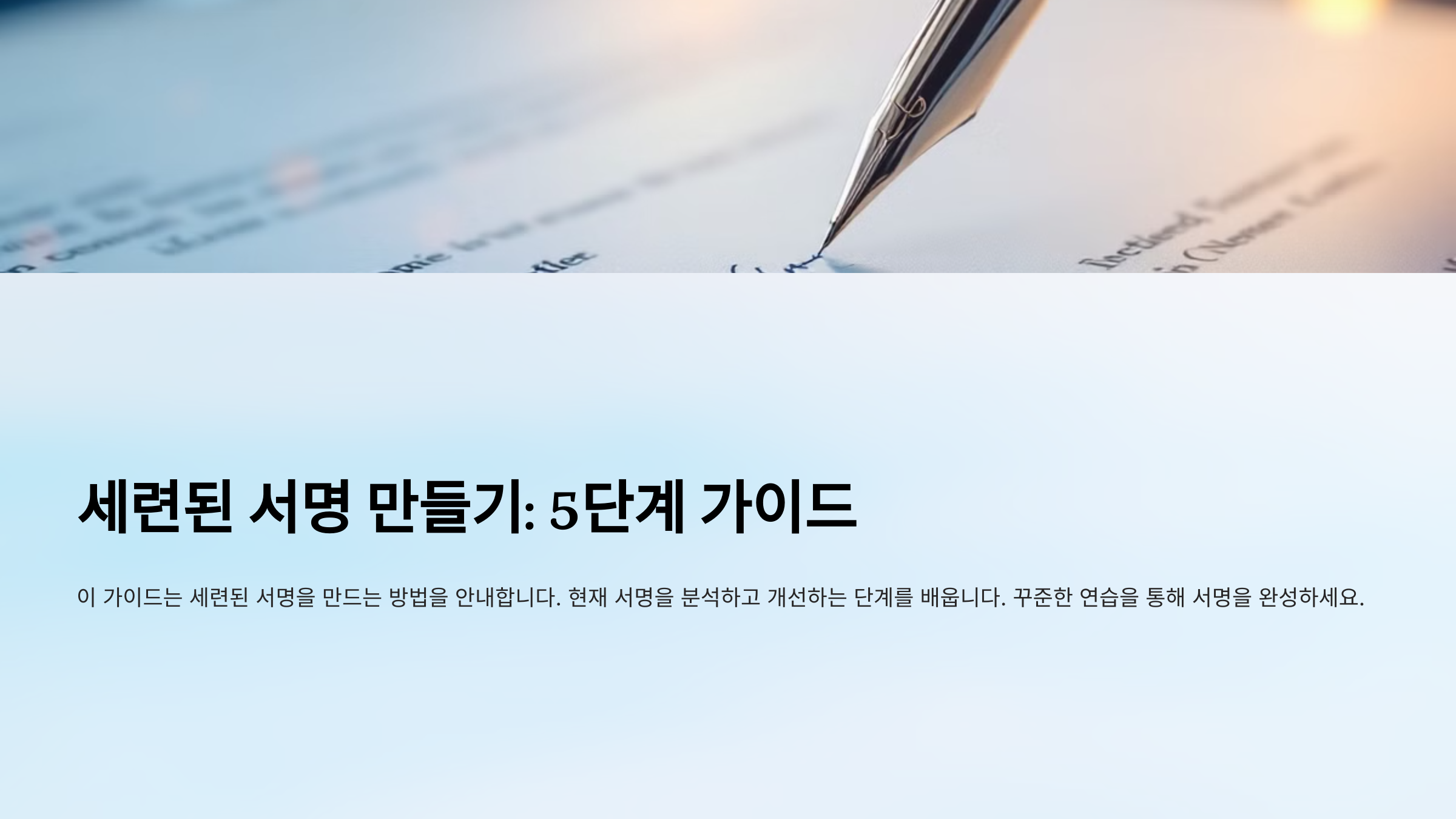
내가 생각했을 때, 멋진 싸인은 간결하면서도 독창적인 스타일을 유지하는 것이 중요해요. 이제 싸인을 세련되게 바꾸는 5단계 과정을 알아볼까요? 🚀
1단계: 현재 싸인 분석하기 🔍
현재 사용하고 있는 싸인이 있다면, 무엇을 개선할 수 있는지 분석하는 것이 첫 단계예요. 싸인을 평가할 때는 가독성, 속도, 디자인, 개성 등 여러 요소를 고려해야 해요. ✍
🔹 현재 싸인 점검 체크리스트
✔ 싸인을 빠르게 쓸 수 있는가?
✔ 동일한 스타일을 유지할 수 있는가?
✔ 내 개성이 잘 드러나는가?
✔ 가독성이 좋고 쉽게 알아볼 수 있는가?
📌 현재 싸인 분석 방법 ✨
분석 요소 확인할 사항 가독성 글자가 알아보기 쉽게 구성되었는가? 속도 5초 이내에 자연스럽게 싸인을 끝낼 수 있는가? 일관성 반복해서 쓸 때 같은 모양을 유지할 수 있는가? 개성 싸인에 나만의 스타일이 담겨 있는가? 이제 2단계: 불필요한 요소 제거를 진행해볼까요? ✂
2단계: 불필요한 요소 제거 ✂
싸인이 복잡하면 빠르게 작성하기 어렵고, 일관성을 유지하기 힘들어요. 따라서 불필요한 장식과 복잡한 획을 줄여주는 과정이 필요해요. ✍🔥
🔹 불필요한 요소 줄이는 방법
✔ 글자의 일부를 단순화하여 빠르게 쓰기
✔ 복잡한 장식(별, 밑줄 등) 제거하기
✔ 글자 간 간격을 조정하여 균형 맞추기
✔ 획을 줄이고 연결을 부드럽게 만들기
📌 단순하고 효율적인 싸인 만들기 ✨
불필요한 요소 개선 방법 복잡한 장식 별, 밑줄, 불필요한 곡선 삭제 획이 너무 많음 획을 최소화하고 간결한 형태 유지 글자 간 간격 불균형 균형을 맞춰 가독성 높이기 글씨체가 너무 꾸밈 필기체를 단순화하여 자연스럽게 변경 이제 3단계: 필기체 흐름 개선을 진행해볼까요? 🖊
3단계: 필기체 흐름 개선 🖊
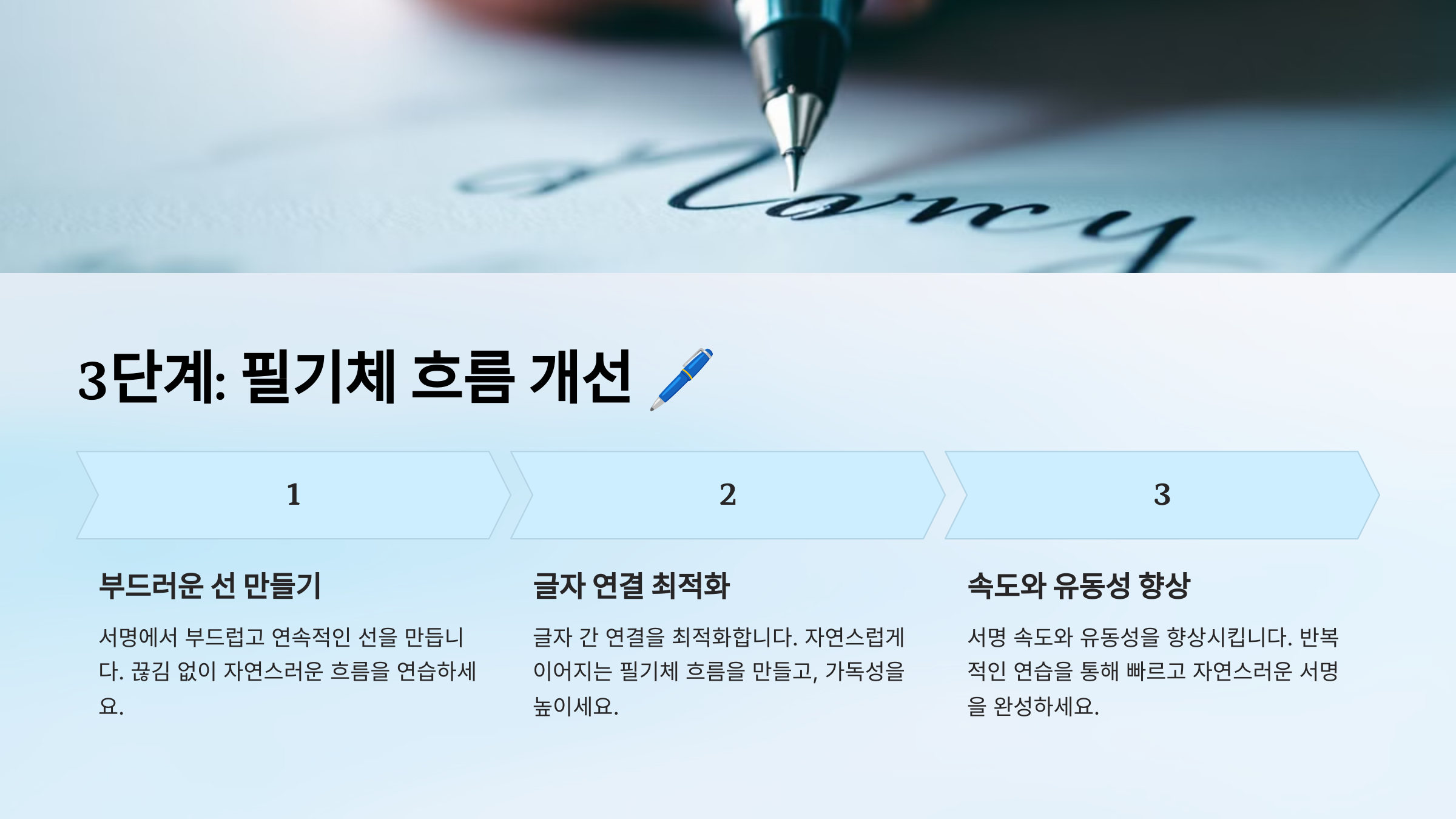
싸인을 세련되게 만들려면 필기체의 자연스러운 흐름이 중요해요. 획을 부드럽게 연결하면 속도가 빨라지고, 싸인이 더 깔끔해 보일 수 있어요. ✍🔥
🔹 필기체 흐름을 개선하는 방법
✔ 글자 간 연결을 부드럽게 이어지도록 연습하기
✔ 곡선을 활용하여 자연스럽게 흐름 만들기
✔ 필기 속도를 높여서 손에 익숙해지도록 연습하기
✔ 이니셜을 강조하고 나머지 글자는 간결하게 정리
📌 부드러운 싸인 흐름 만들기 ✨
필기체 흐름 개선 요소 설명 글자 간 연결 자연스럽게 이어지는 흐름 연습 곡선 활용 부드러운 곡선을 추가해 세련된 스타일 빠른 필기 연습 속도를 높여 자연스러운 흐름 만들기 이니셜 강조 첫 글자를 강조해 강렬한 인상 남기기 이제 4단계: 마무리 스타일 정리를 진행해볼까요? ✨
4단계: 마무리 스타일 정리 ✨
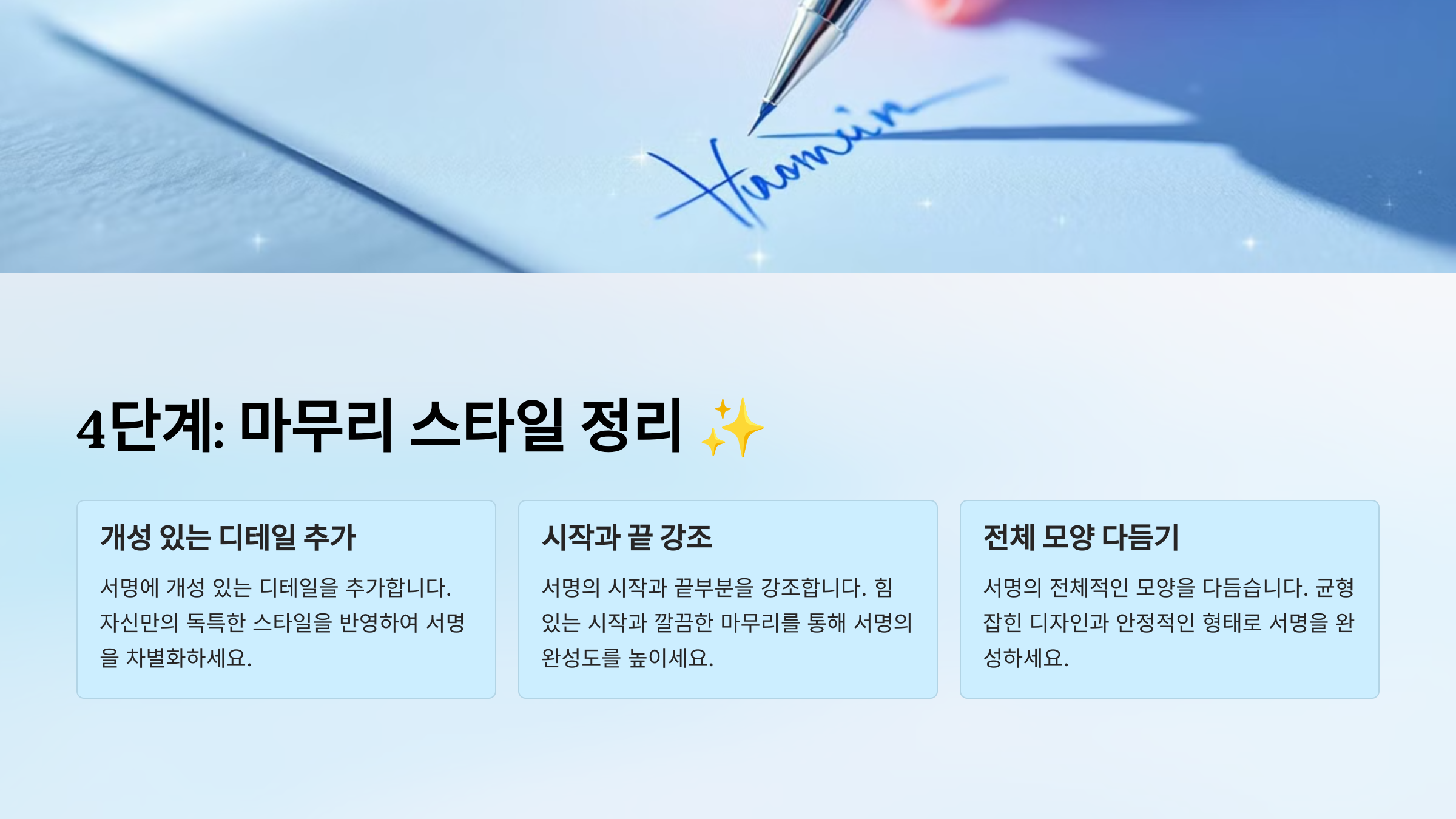
싸인의 마무리 부분은 전체적인 인상을 결정하는 중요한 요소예요. 끝을 어떻게 정리하느냐에 따라 세련된 느낌을 더할 수도 있고, 강렬한 인상을 남길 수도 있어요. ✍🔥
🔹 싸인 마무리를 세련되게 하는 방법
✔ 끝을 길게 빼서 부드러운 흐름 만들기
✔ 마지막 획을 날렵하게 정리하여 강렬한 느낌 주기
✔ 밑줄이나 작은 기호를 활용해 개성을 살리기
✔ 싸인의 크기를 일정하게 유지해 균형 맞추기
📌 싸인 마무리 스타일 ✨
마무리 스타일 설명 끝을 길게 빼기 싸인의 흐름을 부드럽게 이어주는 효과 날렵한 마무리 깔끔하고 강렬한 느낌 연출 기호 활용 별⭐, 점•, 밑줄━ 등을 추가해 개성 표현 균형 유지 싸인의 크기와 배치를 일정하게 유지 이제 5단계: 꾸준한 연습과 정착을 진행해볼까요? 📄
5단계: 꾸준한 연습과 정착 📄
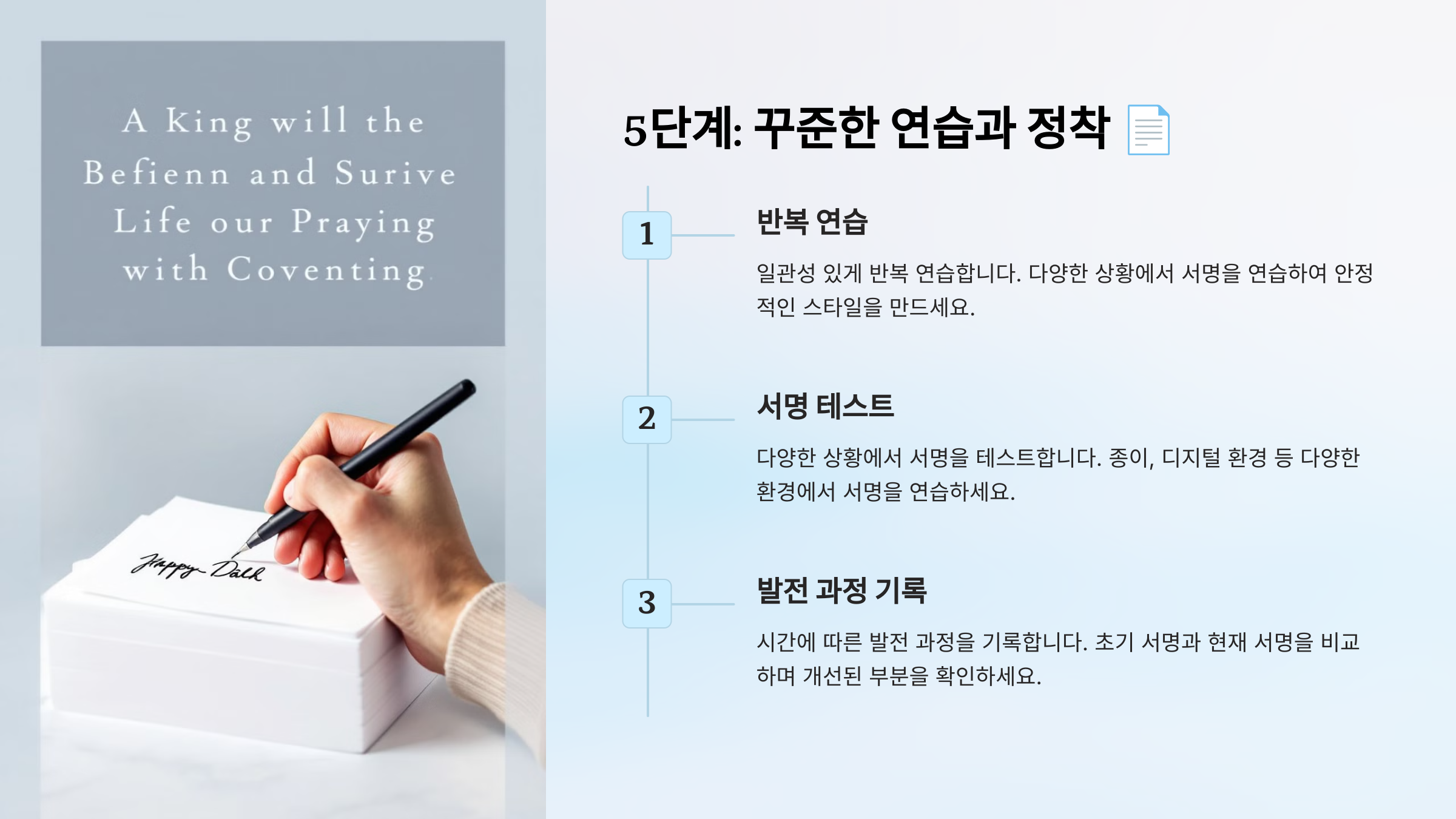
멋진 싸인을 만들었다면 꾸준한 연습을 통해 손에 익히는 과정이 필요해요. 자연스럽게 싸인을 작성할 수 있어야 어떤 상황에서도 일관된 스타일을 유지할 수 있답니다! ✍🔥
🔹 싸인을 정착시키는 방법
✔ 하루 5~10분씩 반복해서 연습하기
✔ 다양한 크기로 싸인을 연습하여 응용력 키우기
✔ 빠르게 작성하는 연습을 통해 자연스럽게 만들기
✔ 공식 문서에서도 동일한 싸인을 유지하도록 연습
📌 효과적인 싸인 연습법 ✨
연습 방법 설명 반복 연습 매일 10번 이상 싸인을 반복해서 연습 크기 조절 A4, 명함, 포스트잇 등 다양한 크기로 작성 속도 향상 5초 안에 싸인을 끝낼 수 있도록 연습 실제 문서 활용 계약서, 서류 등에 실제로 싸인해보기 이제 세련된 싸인 스타일 예시를 살펴볼까요? 🏆
세련된 싸인 스타일 예시 🏆
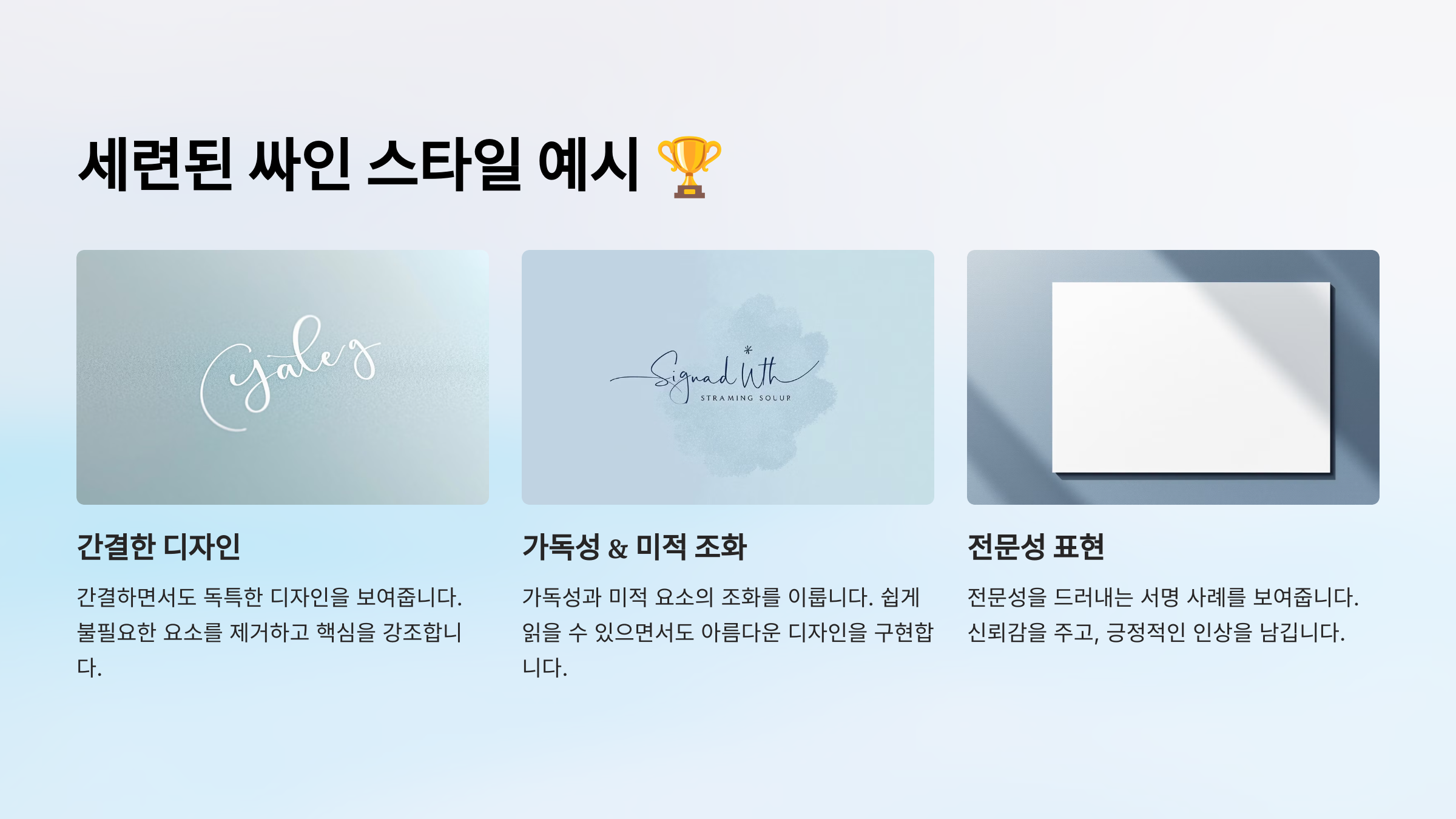
멋진 싸인을 만들기 위해서는 다양한 스타일을 참고하는 것도 좋은 방법이에요. 세련된 싸인은 단순하면서도 개성이 살아 있고, 자연스러운 흐름이 있어야 해요. ✍🔥
🔹 대표적인 싸인 스타일
✔ 이니셜 스타일 – 간결하고 빠르게 작성 가능
✔ 곡선형 스타일 – 부드럽고 자연스러운 느낌
✔ 대문자 강조 스타일 – 강렬한 인상을 남길 수 있음
✔ 미니멀한 스타일 – 단순하지만 고급스러운 느낌 연출
📌 싸인 스타일 비교 ✨
싸인 스타일 설명 이니셜 스타일 이름의 첫 글자만 사용하여 심플하게 구성 곡선형 스타일 부드러운 곡선과 자연스러운 흐름 강조 대문자 강조 이름 전체를 대문자로 강렬하게 표현 미니멀 스타일 불필요한 요소 없이 단순하고 정리된 느낌 이제 싸인에 대한 궁금증을 해결할 시간! FAQ에서 자주 묻는 질문을 정리해볼까요? ❓
FAQ ❓
Q1. 싸인을 더 세련되게 만들려면 어떻게 해야 하나요?
A1. 싸인을 세련되게 만들려면 간결하면서도 개성을 살리는 것이 중요해요. ✔ 이니셜을 강조하여 강렬한 인상 남기기 ✔ 불필요한 장식을 줄이고 자연스러운 흐름 만들기 ✔ 필기 속도를 높여 싸인의 자연스러움 유지하기
Q2. 싸인을 바꾸면 안 좋은 영향이 있을까요?
A2. 개인적인 싸인은 바꿔도 문제없지만, 공식 문서에서 사용하는 싸인은 신중해야 해요. ✔ 은행, 공공기관 등에 등록된 싸인은 변경하려면 업데이트 필요 ✔ 새로운 싸인을 충분히 연습한 후 적용하는 것이 안전
Q3. 싸인을 연습하는 가장 효과적인 방법은?
A3. 꾸준한 연습이 싸인을 자연스럽게 만드는 핵심이에요. ✔ 하루 5~10분씩 반복 연습하기 ✔ A4 용지, 명함 크기 등 다양한 크기로 연습 ✔ 빠르게 써보면서 자연스러운 흐름 익히기
Q4. 싸인에 기호(⭐, ❤, ✔)를 추가해도 괜찮을까요?
A4. 기호를 활용하면 싸인에 개성을 더할 수 있어요. ✔ 별(⭐)이나 밑줄(_)을 활용해 포인트 주기 ✔ 너무 복잡하면 싸인이 길어질 수 있으니 적절한 선에서 활용
Q5. 한글과 영어 싸인을 함께 쓰는 게 좋을까요?
A5. 한글과 영어 싸인을 조합하면 개성과 활용성을 동시에 살릴 수 있어요. ✔ 한글 성 + 영어 이니셜 조합 가능 ✔ 한글과 영어를 자연스럽게 연결하는 방식도 효과적
Q6. 디지털 서명과 수기 싸인을 동일하게 만드는 방법은?
A6. 태블릿이나 스타일러스 펜을 활용하면 디지털과 수기 싸인의 일관성을 유지할 수 있어요. ✔ Adobe Sign, DocuSign 같은 전자 서명 도구 활용 ✔ PNG 파일로 저장하여 문서에 삽입 ✔ 종이에 연습한 싸인을 디지털에서도 동일하게 재현
Q7. 싸인 크기는 어떻게 조절하는 게 좋을까요?
A7. 문서에 맞는 싸인 크기를 조절하는 것이 중요해요. ✔ 계약서, 공식 서류에는 작은 크기로 간결하게 ✔ 팬 사인회나 명판에서는 크게 써서 강한 인상 남기기
Q8. 싸인을 쉽게 기억할 수 있도록 만드는 방법은?
A8. 기억에 남는 싸인은 단순하면서도 독특한 포인트가 있어야 해요. ✔ 첫 글자를 강조하여 강한 인상 남기기 ✔ 부드러운 곡선이나 기호를 활용해 개성 살리기 ✔ 불필요한 요소를 줄이고 빠르게 쓸 수 있도록 디자인하기